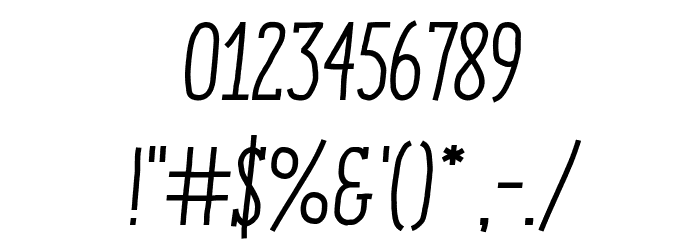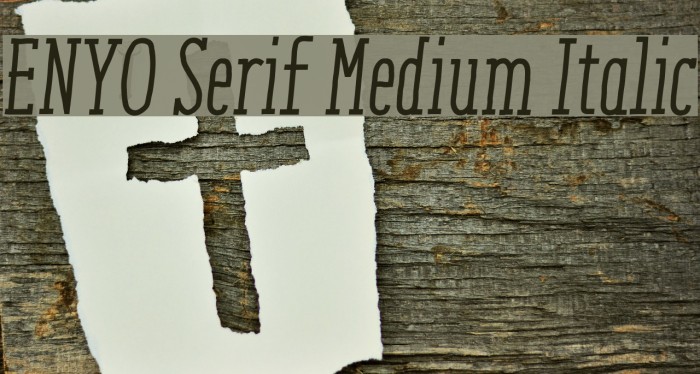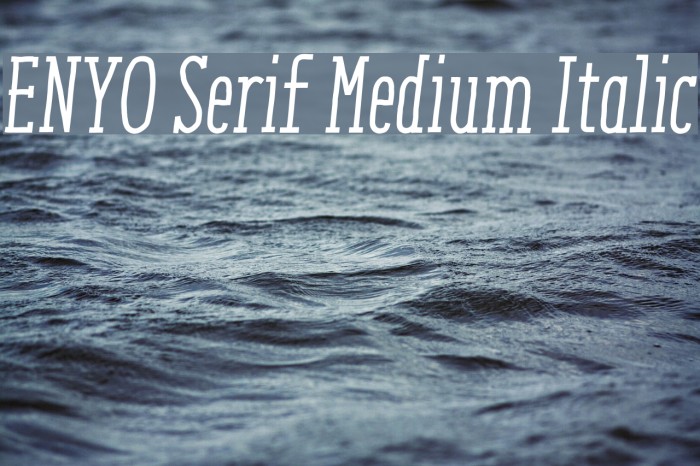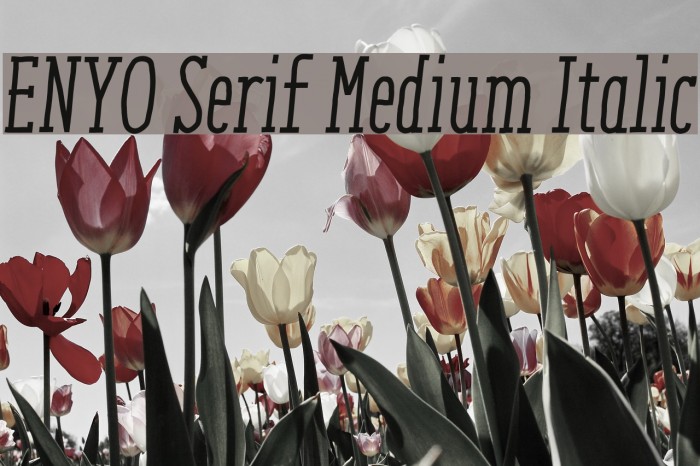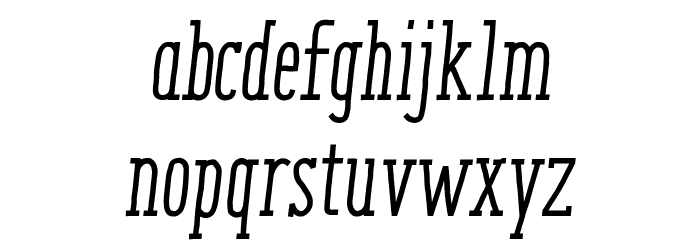
ENYO Serif Medium Italic Font
| Proiecte propuse | Ideal for editorial design, book covers, formal invitations, and branding materials that require a classic yet dynamic touch. |